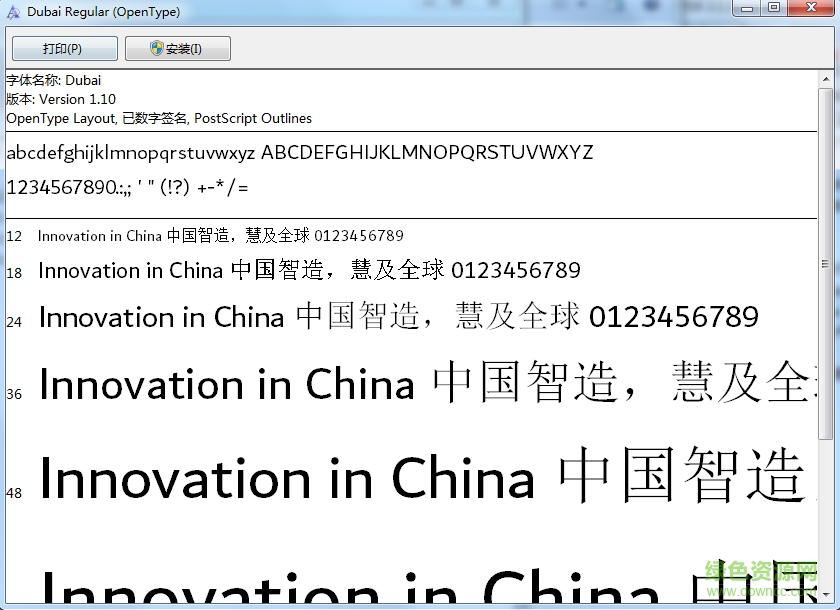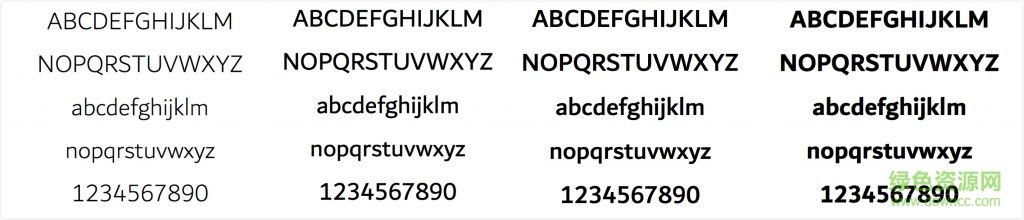
迪拜政府稱(chēng)這款字體的體靈感來(lái)源于迪拜這個(gè)現(xiàn)代化城市本身,可作為“自我表達(dá)的全球媒介”,以此向全世界分享所思所感,捕捉表達(dá)內(nèi)容的所有細(xì)節(jié),反映阿聯(lián)酋期望在創(chuàng)新領(lǐng)域中,成為地區(qū)以至全球領(lǐng)袖的愿景。
“Dubai Font”具有拉丁語(yǔ)和阿拉伯語(yǔ)兩個(gè)版本,適用于 23 種語(yǔ)言,包括細(xì)體、常規(guī)、半粗體和粗體四種字重,同時(shí)也提供了適用于 Windows、Android、Mac OS 的 OpenType TTF 字體格式和適用于 Adobe 的 OpenType CFF 的字體格式,以及 Web 的專(zhuān)用字體格式,供微軟全球 1 億 office 365 的用戶免費(fèi)使用。